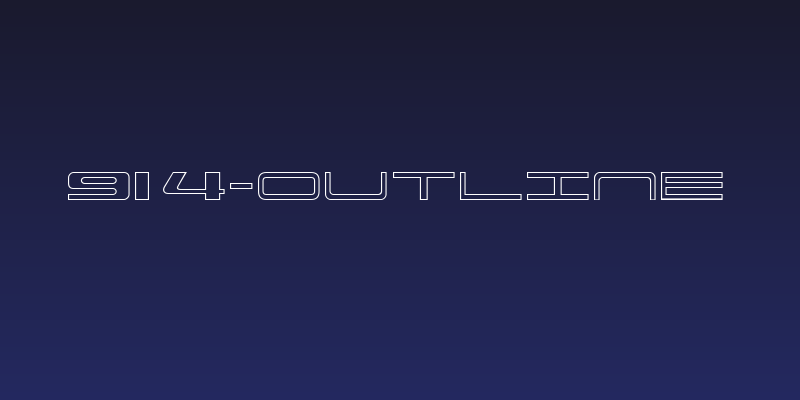
914-OUTLINE Font
✎ Outline
| حالة الاستخدام | Logos, Headlines, Posters |
| مشاريع مقترحة | Ideal for tech-related branding, futuristic designs, digital art projects, and modern advertising campaigns. |